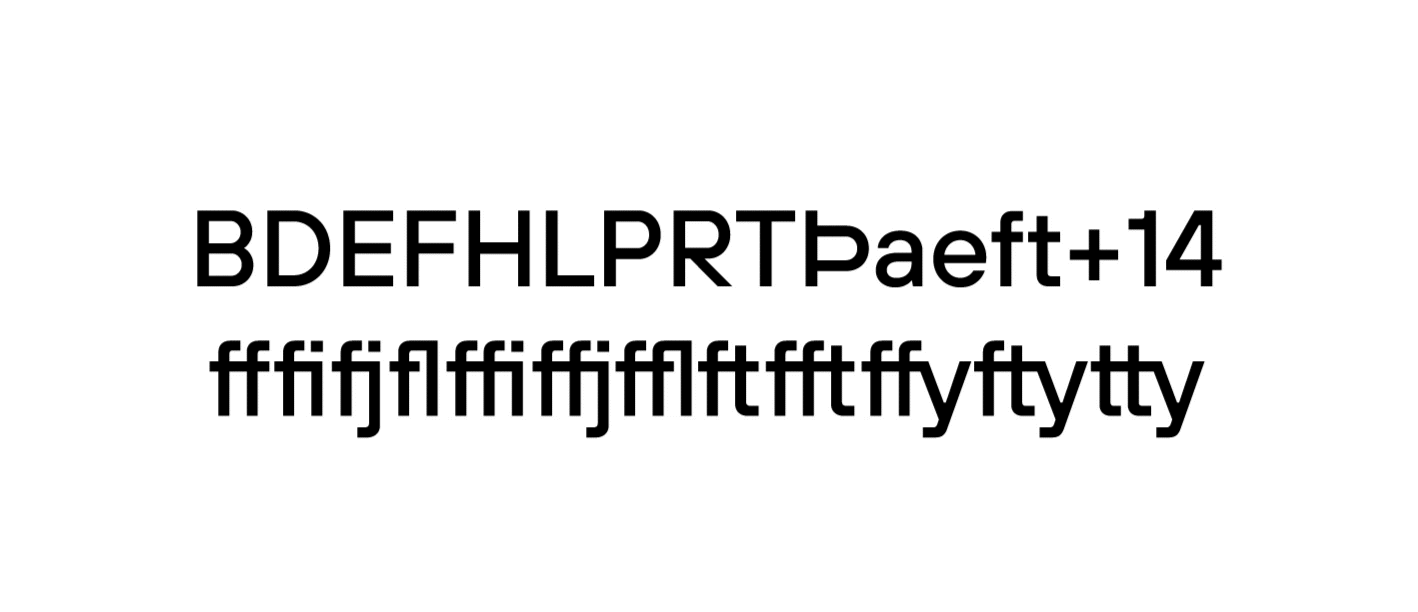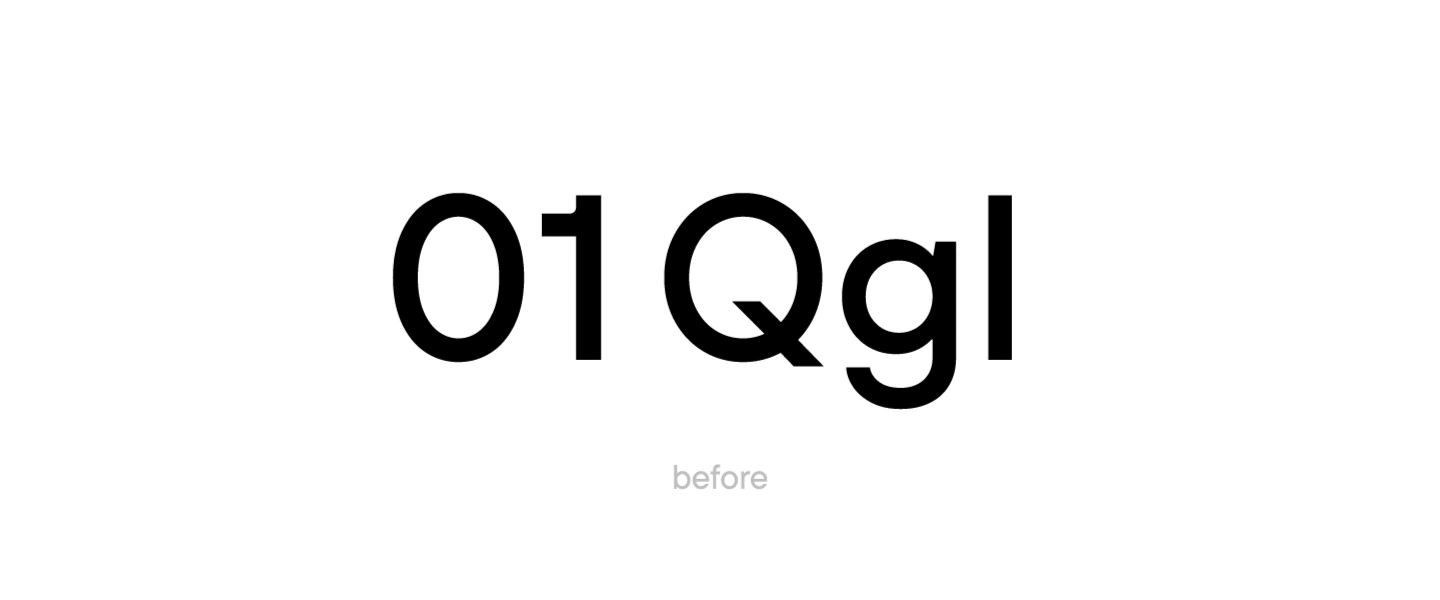
Превращаем TT Hoves Medium в адаптированный TT Hoves GDTI
Брендинговое агентство из Германии Monospace создаёт корпоративный стиль и дизайн для проектов. Компания считает, что благодаря дизайну можно спроектировать бренд, с которым взаимодействие с клиентами будет приятным и долгосрочным.
Компания Monospace хотела внести изменения в шрифт TT Hoves Medium.
Кастомизация охватила несколько областей:
• требовалось внести правки в графику некоторых знаков и сделать акцидентную версию TT Hoves Medium;
• отрисовать и встроить в шрифтовой файл два логотипа компании;
• установить по умолчанию альтернативные формы знаков 0, 1, Q, g, l;
• сократить кассовый состав шрифтового файла: удалить кириллицу, капитель, расширенный состав цифр и символов;
• изменить название шрифта на TT Hoves GDTI.
Команда дизайнеров и технических специалистов TypeType приступила к кастомизации.
Дизайнер изменил графику 39 исходных глифов в одном из начертаний. Дополнительно изменилось начертание глифов с диакритикой.
Кастомизация глифов
Технические специалисты TypeType поменяли местами альтернативные знаки и основные.
Замена основных знаков на альтернативные
Шрифтовой файл пополнился двумя логотипами компании.
Добавление логотипов
Сам шрифтовой файл стал легче: кассовый состав шрифта был уменьшен с 1384 знаков до 656.
Перед отправлением клиенту команда сделала автоматический хинтинг шрифта, а название изменилось на TT Hoves GDTI.
В процессе работы появилось ещё одно дополнение в изменении шрифта: компания захотела дополнительно кастомизировать текстовую версию TT Hoves. В итоге альтернативные формы знаков 0, 1, Q, g, l поставили по умолчанию в 8 разных начертаниях TT Hoves, то есть в 4 прямых и в 4 италиках. Эта версия шрифта тоже получила новое название TT Hoves GDTI Text.
В итоге TypeType предоставило компании Monospace Albert & Buettner GbR кастомизированные версии акцидентного и текстового шрифтов TT Hoves с облегчённым кассовым составом, новой графикой некоторых глифов и новыми названиями.